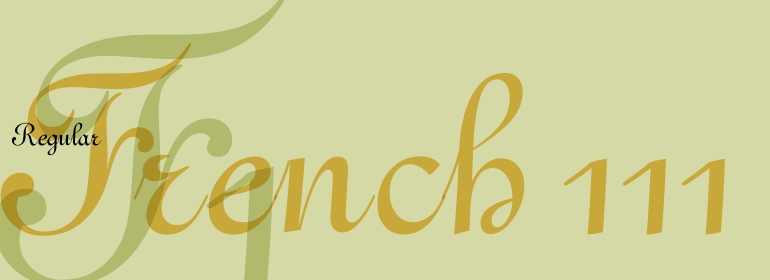
French 111
French 111,这款字体结构工整、笔画清晰,兼顾美观与易读性,适用于标题、正文、海报、包装、LOGO 等多种场景。字形优雅稳定,风格百搭耐看,适配日常排版与创意设计,让文字呈现更舒适、更具质感。French 111一笔一画,皆是细节,以均衡的比例、流畅的线条打造舒适视觉体验,字形端正大气,风格简约现代。无论是商业设计、品牌宣传还是日常排版,都能轻松驾驭,让文字更有格调与力量。French 111字体下载。
字体品牌: Bitstream(Monotype) 设计师:Gando,Nicholas; Hunziker,Hans; Carter,Matthew 字体分类: 字体属性:外文 字符集:Unicode 发布时间: 2018